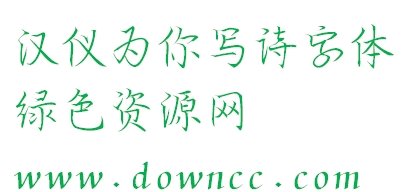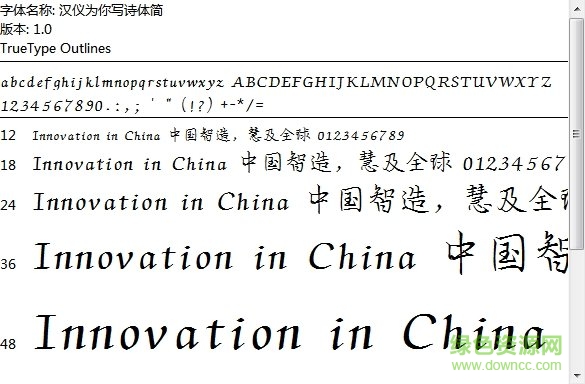
qq為你寫詩字體是漢儀字庫推出的一款干凈流暢的手寫字體,字跡連貫而不凌亂、剛硬而兼具溫婉之氣,給人極其舒適的視覺效果,讓文字更彰顯獨(dú)特色古風(fēng)韻味,綠色資源網(wǎng)獨(dú)家推薦!
豪情萬丈,詩意人生!
詩情寫意盡瀟灑,落筆從容自風(fēng)流!
為你寫詩字體,不同于一般繾綣文弱之氣,字跡盡顯剛正不屈之態(tài),起承轉(zhuǎn)合建柔軟相間,讓文字結(jié)合剛?cè)嶂溃梢詮V泛運(yùn)用于屏幕設(shè)計(jì)、藝術(shù)策劃、廣告創(chuàng)意、印刷排版等領(lǐng)域之中!